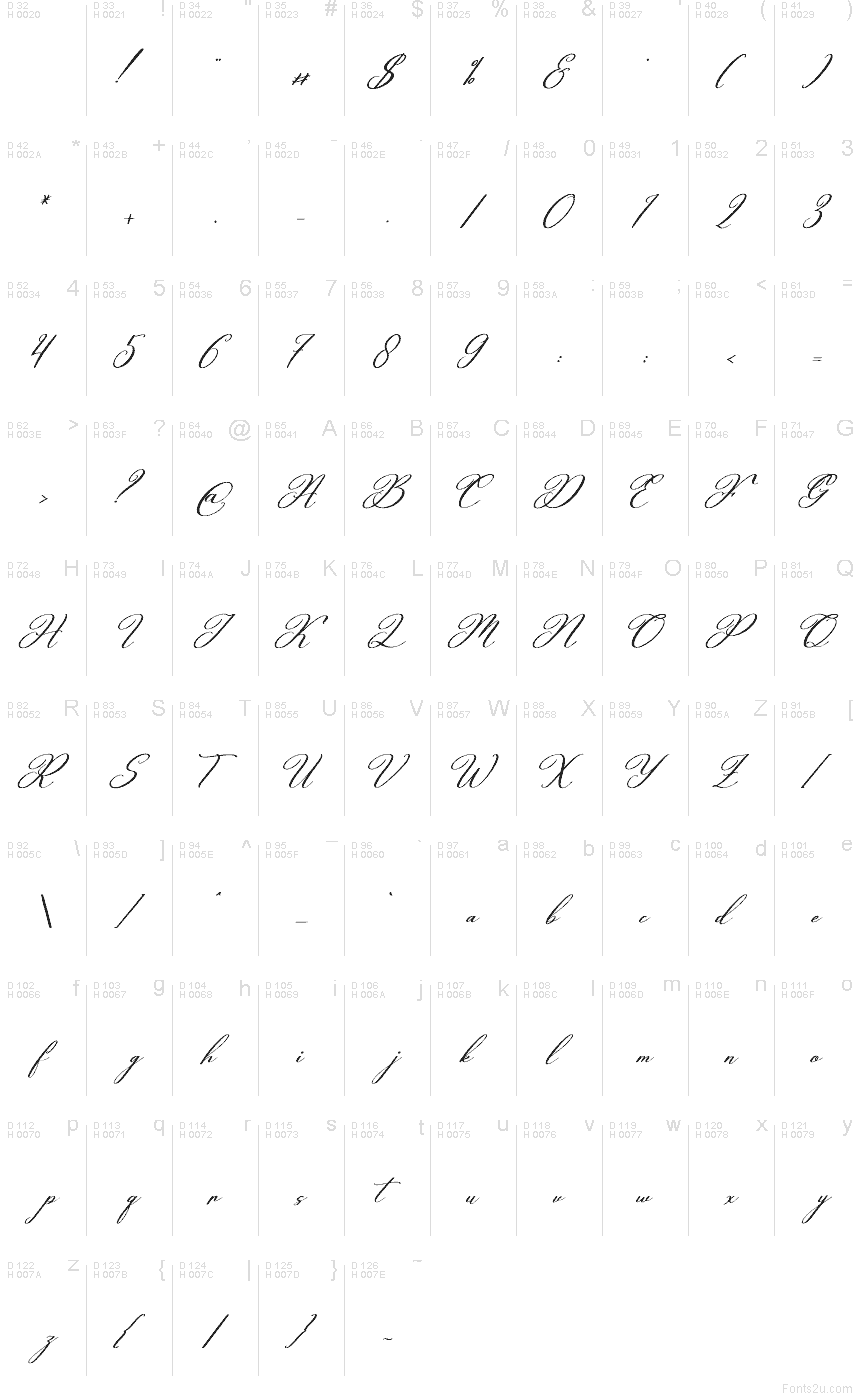
Celtaniya Bioffany Italic od Gracetype Studios je bezplatné kaligrafické písmo definované dlouhými oválnými smyčkami, strmým sklonem a rozmáchlými vstupními tahy, které písmu dodávají vznešenou, slavnostní siluetu. Velká písmena se natahují do širokých oblouků, zatímco malá písmena zůstávají lehčí a plynulejší, čímž vytvářejí kontrast, který působí spíše jako elegantní rukopis na formálních pozvánkách než jako běžný skript.
Díky této vyváženosti je silnou volbou pro svatební tiskoviny, branding parfémů či šperků, záhlaví certifikátů, butikové balení a loga ve stylu podpisu. Prodloužené smyčky a vzdušné tahy poskytují krátkým názvům a titulkům prostor k dýchání, zejména v rozvrženích, která vyžadují vytříbený ústřední prvek namísto hustého textu.